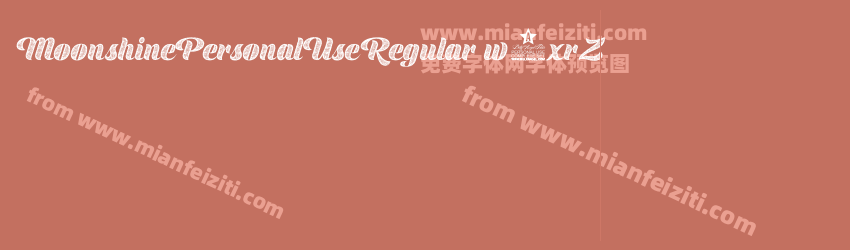
Moonshine Personal Use Regular w1xrZ
字体名称: Moonshine Personal Use Regular w1xrZ
Postscript名称: MoonshinePersonalUse-Regular
本款“Moonshine Personal Use Regular w1xrZ”是一款书写很新颖的字体,字体大方,适合各种设计作品使用!欢迎下载!